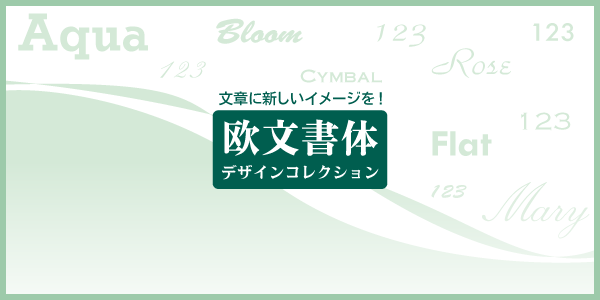
Pr6仕様ならびにPro仕様OpenTypeフォント
モトヤ明朝6・モトヤゴシック6発売および発売記念キャンペーン開催のお知らせ(2023/10/20)
株式会社モトヤでは、10月20日にモトヤ明朝6・モトヤゴシック6の
Pr6仕様OpenTypeフォント(Adobe-Japan1-6準拠)ならびにPro仕様OpenTypeフォント(Adobe-Japan1-4準拠)を
発売いたします。
Pr6仕様ならびにPro仕様OpenTypeフォントは、販売中の
Std仕様OpenTypeフォント(Adobe-Japan1-3準拠)の文字セットを拡張した商品になります。
本製品は、異体字切り換えの技術であるIVS(異体字シーケンス)に対応しており、
IVSに対応したOSとアプリ(※)を組み合わせて使用することで、異体字セレクタによる異体字切り換えが可能です。
また、それぞれPr6N/Pr6フォント・ProN/Proフォント(JIS2004字形/JIS90字形)の2種類のセット販売となります。
※OS、アプリケーションがIVSに対応している必要があります。
弊社ブースでは、高い可読性・視認性・判読性を実現するJIS X0213対応ユニバーサルデザイン(UD)フォント、
低容量で機器組込みに最適なビットマップフォント、デジタル放送の最新規格ARIB STD-B62対応フォントなど、
モトヤフォントの最新情報をご紹介いたします。
| モトヤUDフォント | ユニバーサルデザイン(UD)対応モトヤフォント |
| モトヤICT教科書体 | デジタル教材での見やすさを向上した教科書体 |
| JIS X0213:2004対応フォント | JIS2004対応フォントが新たにUD対応 |
| ビットマップフォント | 組込み用UDビットマップフォント |
| モトヤARIB対応フォント | 4K・8K対応ARIB規格STD-B62準拠フォント |
| モトヤフォントの導入事例 | 組込み機器などモトヤフォントの導入事例の紹介 |
新書体「モトヤワルツ5」発売のお知らせ(2023/07/07)
モトヤの新書体「モトヤワルツ5」の発売についてお知らせいたします。
「モトヤワルツ」は、ゲームやコミックといったポップカルチャーでの使用を想定して開発されました。
月の満ち欠けをモチーフにした特徴的なアクセントと、全体的に少しいびつなバランスが、レトロな雰囲気と共に
独特のリズム感をかもし出し、そのキャッチーな表情の中にダークな印象をも感じさせる、不思議な味わいの書体です。
【モトヤLETS】「モトヤ欧文書体 デザインコレクション」提供開始のお知らせ
モトヤLETS会員様向けに「モトヤ欧文書体デザインコレクション」のダウンロード提供が2023年7月5日より開始されました。
「モトヤ欧文書体 デザインコレクション」は、当社が過去に活字ならびに自社組版機向け専用フォントとして